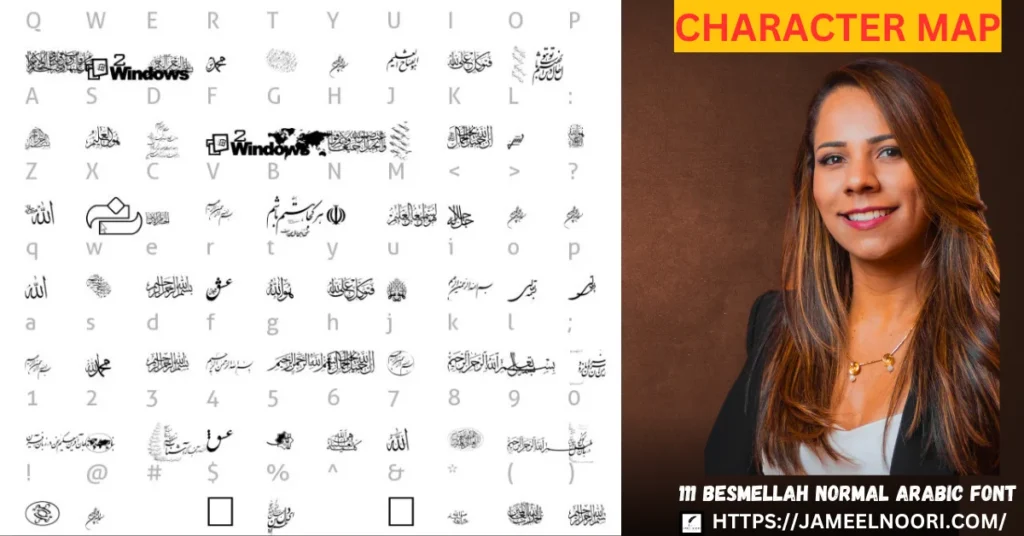
111 Besmellah Normal Arabic Font – Best & Latest Normal Arabic Font
111 Besmellah Normal Arabic Font aik bohot hi mashhoor Normal TrueType Arabic font hai jo Pakistan me magazines, bloggers, designers aur students bohot ziada use karte hain. Ye font apni elegant calligraphy, smooth curves aur stylish Arabic typeface ki wajah se design industry me bohot popular hai. Roman Urdu users is font ko headings, banners, thumbnails aur social media posts me effectively use karte hain.
Why 111 Besmellah Normal Arabic Font Is the Best Choice?
111 Besmellah Normal aik unique Arabic font hai jo readability aur beauty dono combine karta hai. Pakistan ke designers is font ko Urdu fonts, Arabic fonts, aur best Arabic font collections ke saath frequently use karte hain. Ye font lightweight hai, kisi bhi software me smoothly load hota hai aur har platform ke sath compatible hota hai.
Key Reasons:
• Elegant Arabic calligraphy
• Background designs ke liye best choice
• Magazine layout aur branding me widely used
111 Besmellah Normal Arabic Font character map showing complete glyphs and calligraphy shapes
Character map of 111 Besmellah Normal Arabic Font displaying unique Arabic glyphs and calligraphy strokes.
Latest Features of 111 Besmellah Normal Arabic Font
Is font ke features ise “expert choice” banate hain. Calligraphy Arabic style me bohot sharp aur stylish lagti hai. Typeface ki clarity ki wajah se ye blog thumbnails aur social media graphics me perfect suit karta hai.
Best Usage of 111 Besmellah Normal Arabic Font for Designers
Pakistan me is font ka istemaal specially branding aur Islamic content ke liye hota hai. Jo bloggers Arabic font download search karte hain wo aksar is font ko prefer karte hain kyun ke ye elegant aur professional look deta hai.
Ideal Usage Areas:
• Islamic Quotes Designs
• YouTube Thumbnails
• Magazine Titles
• Arabic Posters
• Elegant Calligraphy Projects
Agar aap character map check karein to aapko unique shapes, curves aur calligraphy strokes nazar aayenge jo isi font ko doosron se different banate hain.
Conclusion – Why You Should Choose This Font?
111 Besmellah Normal Arabic Font Pakistan me trending fonts me se aik hai jo readability, design quality aur compatibility ki wajah se designer community ka favorite ban chuka hai. Agar aap best Arabic fonts ki talash me hain to ye font aapko definitely amazing results dega. Ye font har platform me smoothly work karta hai aur beginners ke liye bhi easy-to-use hai.
What is 111 Besmellah Normal Arabic Font?
It is a Normal TrueType Arabic font used for elegant calligraphy and digital design.
Is it suitable for Islamic calligraphy?
Yes, it is one of the best Arabic fonts for Islamic designs.